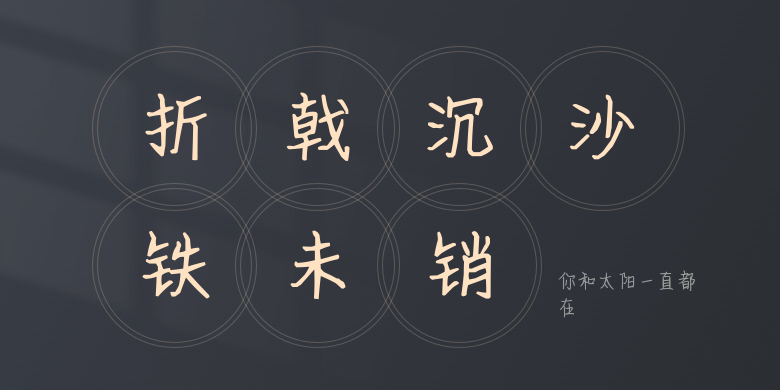
你和太阳一直都在
你和太阳一直都在,这款字体结构工整、笔画清晰,兼顾美观与易读性,适用于标题、正文、海报、包装、LOGO 等多种场景。字形优雅稳定,风格百搭耐看,适配日常排版与创意设计,让文字呈现更舒适、更具质感。你和太阳一直都在一笔一画,皆是细节,以均衡的比例、流畅的线条打造舒适视觉体验,字形端正大气,风格简约现代。无论是商业设计、品牌宣传还是日常排版,都能轻松驾驭,让文字更有格调与力量。你和太阳一直都在字体下载。